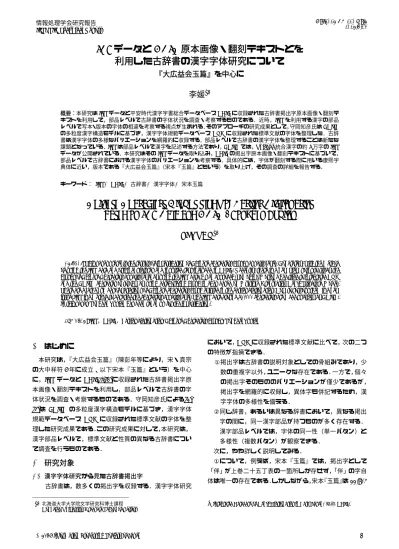
IDSデータとHDIC原本画像・翻刻テキストとを利用した古辞書の漢字字体研究について-『大広益会玉篇』を中心に-
(2) Vol.2016-CH-110 No.6 2016/5/14. 情報処理学会研究報告 IPSJ SIG Technical Report の掲出字が収録される. 「伴」の旁の「半」を含む掲出字は, 「半」 ・ 「畔」 ・ 「伴」などの 21 字がある.原本画像では, 「半」 /「. 」/「. 」との字体があることも確認できる.. 2.3 HDIC 原本画像・翻刻テキスト HDIC では,原本画像から一文字ごとに切り出した画像 を対象としてデータベース化した.掲出字画像データベー. ②は,古辞書において漢字部品レベルで,字体の同一性. スは,漢字字体史研究に利用することを目的として作成し. と多様性とを観察することである.同一性について,同じ. はじめたものである[4].掲出字画像データベースを構築し. 辞書,あるいは異なる辞書の間に,単一パタンだけ存在す. て,掲出字のテキスト入力の効率化をはかる.そして,掲. る部品がある.これらの部品の字体は,同一性があると言. 出字画像データベースによって,掲出字の字形の細部を観. える.多様性について,部品によって,二種類の状況があ. 察できる.宋本玉篇データベースについて,HDIC のプロ. る.一つは,同じ辞書の中バリエーションがあるものであ. ジェクトでは,2014 年にその掲出字と注文とを入力済みで. る.例えば, 「糸」の字体は,高山寺本『篆隷万象名義』の. ある.その後,一次点検・校正の上,宋本『玉篇』のテキ. 「纟」 ・ 「 中,. 」が共存する.もう一つは,一つの辞書では. ストを試行公開中[c]であり,筆者は担当者である.今回の. 同一パタンであるが,異なる辞書の間バリエーションが観. 調査は,試行公開中の掲出字テキストを利用したものであ. 察できる.例えば, 「⺼」の字体は,高山寺本『篆隷万象名. る.宋本玉篇データベースの原本画像は宮内庁書陵部に所. 義』の中, 「⺼」の単一パタンであるが,天治本『新撰字鏡』. 蔵する宋版テキストによった.. の中,「肉」に近い字体である.高山寺本『篆隷万象名義』 と天治本『新撰字鏡』とでは, 「⺼」の多様性が確認できる. さらに,HDIC に収録された古辞書は,古写本と古版本 とがある.古写本は,字体のバリエーションが豊富であり,. 3. 漢字部品に関連する漢字字体の先行研究 漢字字体上の相異が問題になる漢字部品レベルのものが,. 同時に誤写や誤脱を含むものである.原本『玉篇』,高山寺. 今まで関連する各領域の研究成果がある.人文学では,. 本『篆隷万象名義』,天治本『新撰字鏡』,図書寮本『類聚. [5][6][7]は,後漢から魏晋まで,魏晋から隋唐までの書体・. 名義抄』,観智院本『類聚名義抄』はいずれも古写本である.. 字体変化の視点から,多くの実例を集め,『篆隷万象名義』. 古版本は,字体のバリエーションが少なくなり,写本より. の俗字の分析を行い,所用の俗字を共通する文字ごとに. 印刷が鮮明である.掲出字の解読が写本よりしやすい面が. 250 種類に分類した.情報処理では,JIS の包摂規準と UCS. ある.宋本『玉篇』は古版本である.HDIC の作業は,宋本. の IWDS(IRG Working Document Series)が挙げられる.. 『玉篇』の掲出字テキストデータベースを作成し,これを. 守岡知彦氏による[2]は HNG に収録された代表字形デー. 土台として古写本の辞書の作業を進める方針をとっている. タへの IWDS-1[d]を適用した場合の包摂可能性を検討した.. [4].また,字体が翻刻する際に用いる康熙字典体も宋本『玉. 本研究は IDS データを通して,部品レベルで宋本『玉篇』. 篇』に近い.そこで,本研究は古版本である宋本『玉篇』. の掲出字の原本字体の同一性と多様性とを考察するもので. を取り上げ,その漢字字体の実態を考察する.そして,宋. ある.そして,宋本玉篇データベースにおける掲出字符号. 本『玉篇』データベースにおける掲出字符号化する際の包. 化の暗黙的な包摂の実際を整理することによって,包摂規. 摂の実際を整理する.. 準を明確化させようとする.. 2.2 IDS データ. 4. 漢字部品リストの抽出. IDS は部品レベルで漢字を記述する方法である.Unicode では 12 個の漢字構成記述文字 IDC(Ideographic Description Character,⿰⿱⿲⿳⿴⿵⿶⿷⿸⿹⿺⿻,U+2FF0〜U+2FFB) を提供し,これらの IDC によって漢字部品の位置関係を示 すことができる.CHISE では,Unicode 統合漢字の約 7 万 字の IDS データが公開されている[b].IDS は,翻刻の際に, 符号化できない難字を表現する手段である.一方で,大多 数の漢字が IDS データによる記述があるため,IDS データ によって,漢字の部品検索ができる.原本画像と併用する ことによって,部品の原本字体を確認の実現することが可 能となっている.. b) CHISE 漢字構造情報データ http://kanji.zinbun.kyotou.ac.jp/projects/chise/ids/ c) http://hdic.jp d) List of UCV (Unifiable Component Variations) of Ideographs. ⓒ2016 Information Processing Society of Japan. 調査手順は,まず IDS データによって,漢字を構成する 部品を整理する.次に,抽出した漢字の部品を手がかりに して,HDIC の掲出字原本画像・翻刻テキストに基づき,宋 本玉篇における漢字字体のバリエーションを考察する. CHISE で公開する Unicode 統合漢字・基本多言語面の IDS データを利用し,Excel で繰り返してマッチング作業を行 う.この手順によって,次の 534 個のさらに分割できない 基本漢字部品[e]を得られた.ただし,これらの部品の中で は,簡体字による部品も混在し,選別する抽出作業が必要 となる.これらの部品を対象として,宋本『玉篇』の掲出 字の原本字体の調査を行う.. e) なお今回の調査,「咅」のような中間部品や符号化されていない CDP 外 字(台湾中央研究院)などを対象外とした.. 2.
(3) Vol.2016-CH-110 No.6 2016/5/14. 情報処理学会研究報告 IPSJ SIG Technical Report 1. 2. 3. 4. 5. 6. 7. 8. 9. 10. 来. 來. 耂. 老. 乐. 了. 耒. 力. 立. 吏. タ. ⺄. ⺅. ⺆. ⺇. ⺉. ⺊. ⺌. ⺖. ⺘. 241. 242. 243. 244. 245. 246. 247. 248. 249. 250. 11. 12. 13. 14. 15. 16. 17. 18. 19. 20. 隶. 冫. 両. 两. 龙. 龍. 鹵. 鹿. 率. 麻. ⺡. ⺢. ⺣. ⺧. ⺨. ⺩. ⺪. ⺫. ⺭. ⺮. 251. 252. 253. 254. 255. 256. 257. 258. 259. 260. 21. 22. 23. 24. 25. 26. 27. 28. 29. 30. 马. 馬. 𦣝. 毛. 矛. 戼. 门. 門. 米. 糸. ⺯. ⺲. ⺳. ⺶. ⺼. ⻀. ⻃. ⻊. ⻌. ⻏. 261. 262. 263. 264. 265. 266. 267. 268. 269. 270. 31. 32. 33. 34. 35. 36. 37. 38. 39. 40. 丏. 黾. 民. 皿. 黽. 末. 母. 木. 目. 乃. ⻖. ⻗. ⻞. ⻢. ⻤. 凹. 八. 巴. 𡗜. 犮. 271. 272. 273. 274. 275. 276. 277. 278. 279. 280. 41. 42. 43. 44. 45. 46. 47. 48. 49. 50. 內. 内. 年. 卄. 廿. 鸟. 鳥. 乜. 肀. 帇. 白. 办. 半. 勹. 宀. 贝. 貝. 本. 匕. 比. 281. 282. 283. 284. 285. 286. 287. 288. 289. 290. 51. 52. 53. 54. 55. 56. 57. 58. 59. 60. 牛. 牜. 女. 爿. 皮. 片. 丿. 朩. 𣎳. 冖. 必. 㡀. 畢. 釆. 髟. 豳. 秉. 疒. 癶. 卜. 291. 292. 293. 294. 295. 296. 297. 298. 299. 300. 61. 62. 63. 64. 65. 66. 67. 68. 69. 70. 平. 攴. 七. 齐. 齊. 千. 凵. 欠. 且. 青. 不. 才. 艹. 艸. 刂. 冊. 册. 𠕋. 𢆍. 臿. 301. 302. 303. 304. 305. 306. 307. 308. 309. 310. 71. 72. 73. 74. 75. 76. 77. 78. 79. 80. 靑. 丘. 求. 曲. 犬. 隺. 冄. 冉. 人. 刄. 丳. 镸. 長. 厂. 车. 車. 屮. 臣. 辰. 承. 311. 312. 313. 314. 315. 316. 317. 318. 319. 320. 81. 82. 83. 84. 85. 86. 87. 88. 89. 90. 日. 禸. 肉. 入. 卅. 三. 彡. 色. 山. 㚒. 乗. 乘. 尺. 齿. 齒. 彳. 斥. 赤. 虫. 丑. 321. 322. 323. 324. 325. 326. 327. 328. 329. 330. 91. 92. 93. 94. 95. 96. 97. 98. 99. 100. 譱. 丄. 上. 舌. 申. 𦥔. 身. 生. 尸. 𠃜. 豖. 川. 巛. 舛. 串. 垂. 埀. 辵. 朿. 寸. 331. 332. 333. 334. 335. 336. 337. 338. 339. 340. 101. 102. 103. 104. 105. 106. 107. 108. 109. 110. 十. 饣. 石. 史. 矢. 豕. 士. 氏. 礻. 示. 大. 歹. 亻. 卩. 丹. 刀. 丶. 电. 弔. 𢎨. 341. 342. 343. 344. 345. 346. 347. 348. 349. 350. 111. 112. 113. 114. 115. 116. 117. 118. 119. 120. 世. 丗. 亊. 事. 奭. 手. 𦣻. 首. 𠘧. 书. 丁. 鼎. 东. 東. 兜. 斗. 豆. 鬥. 𠁁. 𠂤. 351. 352. 353. 354. 355. 356. 357. 358. 359. 360. 121. 122. 123. 124. 125. 126. 127. 128. 129. 130. 疋. 鼡. 黍. 鼠. 丨. 束. 爽. 水. 氺. 厶. 歺. 噩. 儿. 而. 耳. 二. 犭. 攵. 匚. 方. 361. 362. 363. 364. 365. 366. 367. 368. 369. 370. 131. 132. 133. 134. 135. 136. 137. 138. 139. 140. 巳. 罒. 四. 肃. 粛. 肅. 夊. 𣥂. 田. 㐁. 飞. 非. 飛. 丰. 风. 風. 𦈢. 缶. 夫. 乀. 371. 372. 373. 374. 375. 376. 377. 378. 379. 380. 141. 142. 143. 144. 145. 146. 147. 148. 149. 150. 冂. 头. 凸. 土. 屯. 瓦. 丸. 万. 卐. 卍. 巿. 弗. 甶. 甫. 父. 阜. 丐. 甘. 干. 髙. 381. 382. 383. 384. 385. 386. 387. 388. 389. 390. 151. 152. 153. 154. 155. 156. 157. 158. 159. 160. 亡. 王. 网. 囗. 韦. 为. 為. 韋. 爲. 未. 戈. 革. 鬲. 艮. 𧰨. 更. 工. 弓. 廾. 谷. 391. 392. 393. 394. 395. 396. 397. 398. 399. 400. 161. 162. 163. 164. 165. 166. 167. 168. 169. 170. 亠. 文. 我. 巫. 无. 毋. 㐅. 乄. 五. 兀. 骨. 瓜. 冎. 乖. 卝. 毌. 丱. 广. 龟. 龜. 401. 402. 403. 404. 405. 406. 407. 408. 409. 410. 171. 172. 173. 174. 175. 176. 177. 178. 179. 180. 戊. 夕. 覀. 西. 习. 匸. 卌. 丅. 下. 㔾. 鬼. 𠃌. 果. 禾. 黑. 乎. 虍. 戸. 互. 戶. 411. 412. 413. 414. 415. 416. 417. 418. 419. 420. 181. 182. 183. 184. 185. 186. 187. 188. 189. 190. 乡. 小. 心. 辛. 玄. 穴. 熏. 丫. 牙. 亚. 户. 黄. 黃. 火. 灬. 丌. 及. 亟. 几. 己. 421. 422. 423. 424. 425. 426. 427. 428. 429. 430. 191. 192. 193. 194. 195. 196. 197. 198. 199. 200. 襾. 亜. 亞. 讠. 严. 言. 訁. 央. 羊. 幺. 彐. 彑. 旡. 㡭. 夹. 夾. 甲. 戋. 柬. 见. 431. 432. 433. 434. 435. 436. 437. 438. 439. 440. 201. 202. 203. 204. 205. 206. 207. 208. 209. 210. 爻. 也. 业. 页. 曳. 頁. 一. 衤. 衣. 乁. 見. 纟. 糹. 角. 孑. 疌. 丯. 巾. 斤. 钅. 441. 442. 443. 444. 445. 446. 447. 448. 449. 450. 211. 212. 213. 214. 215. 216. 217. 218. 219. 220. 夷. 𦣞. 乙. 已. 𠂆. 乂. 弋. 义. 邑. 乚. 金. 釒. 井. 丩. 九. 久. 乆. 韭. 臼. 𦥑. 451. 452. 453. 454. 455. 456. 457. 458. 459. 460. 221. 222. 223. 224. 225. 226. 227. 228. 229. 230. 音. 冘. 乑. 𠃊. 尹. 㐆. 廴. 永. 用. 尢. 巨. 亅. 孒. 孓. 夬. 𢇍. 丂. 口. 㐄. 巜. 461. 462. 463. 464. 465. 466. 467. 468. 469. 470. 231. 232. 233. 234. 235. 236. 237. 238. 239. 240. 尤. 由. 酉. 丣. 又. 于. 㬰. 臾. 鱼. 禺. ⓒ2016 Information Processing Society of Japan. 3.
(4) Vol.2016-CH-110 No.6 2016/5/14. 情報処理学会研究報告 IPSJ SIG Technical Report 471. 472. 473. 474. 475. 476. 477. 478. 479. 480. 魚. 予. 羽. 雨. 禹. 玉. 聿. 円. 曰. 曱. 481. 482. 483. 484. 485. 486. 487. 488. 489. 490. 月. 戉. 龠. 𡿧. 𢦏. 兂. 夨. 甴. 乍. 长. 491. 492. 493. 494. 495. 496. 497. 498. 499. 500. 丈. 爪. 爫. 兆. 乛. 氶. 之. 夂. 止. 黹. 501. 502. 503. 504. 505. 506. 507. 508. 509. 510. 豸. 中. 重. 舟. 州. 竹. 专. 丬. 隹. 子. 511. 512. 513. 514. 515. 516. 517. 518. 519. 520. 自. 辶. 𠂇. 阝. 充. 者. 龰. 龴. 龵. 龶. 521. 522. 523. 524. 525. 526. 527. 528. 529. 530. 龷. 龸. 䒑. 𠆢. 𤰔. 𫩏. 𬜯. 具. 冗. 刃. 531. 532. 533. 534. 叟. 旣. 直. 𥄳. 5. 漢字部品から見た字体のバリエーション 対象となる 438 個の部品を調査したところ,原本字体に より,字体の同一性を示す単一パタンの部品と多様性を示 す複数パタンの字体とに分けられる.次に,実例を示しな がら説明する[f]. 5.1 単一パタン (1). 3⺅. IDS. Entry. ⿰⺅司. 伺. ⿰⺅童. 僮. ⿰⺅二. 仁. ⿰⺅虒. 傂. ⿰⺅丕. 伾. IMG. HDIC の掲出字原本画像・翻刻テキストによって,次の 漢字部品,計 96 個を選別し,漢字字体調査の対象外とす る.これ以外 438 個の漢字部品の調査結果を次節で示す. ・簡体字による部品(27 個) 46. 75. 84. 113. 135. 142. 169. 195. 198. 200. 贝. 车. 齿. 东. 风. 弗. 龟. 夹. 戋. 见. 202. 210. 235. 251. 276. 332. 364. 372. 386. 424. 纟. 钅. 乐. 马. 鸟. 饣. 肃. 头. 为. 讠. 425. 434. 448. 469. 490. 严. 页. 义. 鱼. 长. (2). 6⺉. ・原本字体に含まれない部品(44 個) 17. 33. 35. 69. 71. 97. 110. 127. 131. 139. ⺪. ⻞. ⻤. 𢆍. 丳. 埀. 𢎨. 犭. 飞. 夫. 150. 212. 217. 224. 243. 244. 245. 262. 274. 278. 髙. 釒. 乆. 孓. 両. 两. 龙. 黾. 卄. 乜. 279. 294. 310. 343. 345. 350. 352. 365. 385. 398. 肀. 齐. 刄. 亊. 奭. 书. 鼡. 粛. 韦. 乄. 405. 418. 422. 423. 427. 456. 478. 480. 488. 507. 习. 丫. 亜. 亞. 訁. 㐆. 円. 曱. 甴. 专. 508. 524. 526. 527. 丬. 𠆢. 𫩏. 𬜯. IDS. Entry. ⿰𠮠⺉. 別. ⿰萠⺉. 蒯. ⿰茾⺉. 荆. ⿰肖⺉. 削. ⿰奇⺉. 剞. IMG. ・原本字体に孤例である部品(25 個) 1. 4. 13. 56. 80. 98. 167. 178. 223. 231. タ. ⺆. ⺣. 豳. 承. 辵. 丱. 戸. 孒. 来. 257. 301. 315. 321. 322. 342. 378. 379. 380. 403. 丗. 万. 卐. 卍. 覀. 门. 靑. 卅. 譱. 丄. 406. 407. 420. 484. 522. 匸. 卌. 亚. 𡿧. 龸. 一部の原本字体しか示さないが, 「⺅」と「⺉」の字体 は,宋本『玉篇』ではすべて異同がない.原本字体のレベ ルでは,単一パタンであることが確認できる. 単一パタンであることが確認できた漢字部品は次の 237 個がある.宋本『玉篇』において,これらの部品は,字体 の同一性が確認できた.. f) 例示する「⺅」「⺉」「巴」「甘」等の部品をもちいる掲出字の翻字は, [8]に収録された宋本『玉篇』の翻刻テキストと一致する.. ⓒ2016 Information Processing Society of Japan. 4.
(5) Vol.2016-CH-110 No.6 2016/5/14. 情報処理学会研究報告 IPSJ SIG Technical Report 䒑. 具. 冗. 刃. 旣. 直. 3. 6. 9. 10. 14. 15. 16. 20. 21. 22. ⺅. ⺉. ⺖. ⺘. ⺧. ⺨. ⺩. ⺮. ⺯. ⺲. 25. 27. 28. 29. 30. 31. 32. 36. 39. 45. ⺼. ⻃. ⻊. ⻌. ⻏. ⻖. ⻗. 凹. 𡗜. 宀. 50. 52. 53. 55. 57. 58. 59. 64. 65. 67. 比. 㡀. 畢. 髟. 秉. 疒. 癶. 艸. 刂. 册. 68. 72. 73. 81. 82. 83. 85. 86. 87. 88. 𠕋. 镸. 長. 乗. 乘. 尺. 齒. 彳. 斥. 赤. 89. 91. 92. 94. 100. 102. 103. 104. 108. 109. 虫. 豖. 川. 舛. 寸. 歹. 亻. 卩. 电. 弔. 111. 112. 114. 116. 117. 120. 122. 124. 129. 130. 丁. 鼎. 東. 斗. 豆. 𠂤. 噩. 而. 匚. 方. 132. 133. 134. 136. 137. 145. 149. 152. 154. 155. 非. 飛. 丰. 風. 𦈢. 父. 干. 革. 艮. 𧰨. 156. 157. 160. 161. 162. 166. 168. 173. 180. 181. 更. 工. 谷. 骨. 瓜. 毌. 广. 果. 戶. 户. 184. 185. 187. 188. 194. 197. 201. 203. 209. 211. 火. 灬. 及. 亟. 㡭. 甲. 見. 糹. 斤. 金. 215. 218. 225. 226. 229. 232. 233. 234. 236. 237. 九. 韭. 夬. 𢇍. 㐄. 來. 耂. 老. 了. 耒. 239. 240. 246. 247. 248. 249. 250. 252. 254. 258. 立. 吏. 龍. 鹵. 鹿. 率. 麻. 馬. 毛. 門. 260. 263. 264. 265. 268. 269. 270. 272. 273. 277. 糸. 民. 皿. 黽. 木. 目. 乃. 内. 年. 鳥. 281. 282. 283. 285. 286. 287. 290. 291. 298. 300. 牛. 牜. 女. 皮. 片. 丿. 冖. 平. 欠. 青. 304. 305. 306. 311. 312. 316. 317. 318. 319. 325. 曲. 犬. 隺. 日. 禸. 三. 彡. 色. 山. 申. 326. 327. 328. 330. 331. 333. 334. 336. 337. 338. 𦥔. 身. 生. 𠃜. 十. 石. 史. 豕. 士. 氏. 339. 340. 341. 344. 346. 347. 351. 353. 356. 359. 礻. 示. 世. 事. 手. 𦣻. 疋. 黍. 束. 氺. 361. 362. 367. 374. 375. 381. 382. 384. 387. 389. 巳. 罒. 夊. 土. 屯. 亡. 王. 囗. 為. 爲. 393. 394. 395. 396. 397. 399. 409. 411. 413. 417. 我. 巫. 无. 毋. 㐅. 五. 下. 乡. 心. 熏. 419. 421. 426. 428. 430. 431. 432. 433. 435. 436. 牙. 襾. 言. 央. 幺. 爻. 也. 业. 曳. 頁. 「巴」と「甘」の字体は,宋本『玉篇』ではそれぞれ二. 437. 439. 441. 443. 444. 445. 446. 447. 450. 451. つのパタンが観察される.原本字体レベルでは,複数パタ. 一. 衣. 夷. 乙. 已. 𠂆. 乂. 弋. 乚. 音. ンであることが確認できた.. 453. 455. 460. 466. 470. 473. 475. 479. 483. 489. 複数パタンであることが確認できた漢字部品は次の 201. 乑. 尹. 尢. 于. 禺. 羽. 禹. 曰. 龠. 乍. 個がある.宋本『玉篇』において,これらの部品は,字体. 491. 496. 497. 499. 500. 501. 502. 503. 505. 509. の多様性が確認できる.. 丈. 氶. 之. 止. 黹. 豸. 中. 重. 州. 隹. 511. 512. 513. 514. 515. 516. 517. 519. 520. 自. 辶. 𠂇. 阝. 充. 者. 龰. 龵. 龶. 523. 525. 528. 529. 530. 532. 533. ⓒ2016 Information Processing Society of Japan. 𤰔. 5.2 複数パタン (3) 38 巴 IDS. Entry. ⿰⺼巴. 肥. ⿰. 巴. 𣥘. ⿰立巴. 𥩙. ⿸戶巴. 𢨴. ⿰木巴. 杷. IMG. (4) 148 甘 IDS. Entry. ⿱弋甘. 𤮼. ⿰甘覃. 㽑. ⿰甘兼. 㽐. ⿱. 甘. 甞. ⿱干甘. 𤮻. IMG. 2. 5. 7. 8. 11. 12. 18. 19. 23. 24. 521. ⺄. ⺇. ⺊. ⺌. ⺡. ⺢. ⺫. ⺭. ⺳. ⺶. 龷. 26. 37. 38. 40. 41. 43. 44. 47. 48. 49. ⻀. 八. 巴. 犮. 白. 半. 勹. 貝. 本. 匕. 5.
(6) Vol.2016-CH-110 No.6 2016/5/14. 情報処理学会研究報告 IPSJ SIG Technical Report 51. 54. 60. 61. 62. 63. 66. 70. 74. 76. 438 個の基本部品のうち,237 個の部品に対応する漢字. 必. 釆. 卜. 不. 才. 艹. 冊. 臿. 厂. 車. 字体は宋本『玉篇』において,単一パタンであり,字体の. 77. 78. 79. 90. 93. 95. 96. 99. 101. 105. 同一性が確認できた.201 個の部品に対応する漢字字体は. 屮. 臣. 辰. 丑. 巛. 串. 垂. 朿. 大. 丹. 宋本『玉篇』ではバリエーションが観察され,字体の多様. 106. 107. 115. 118. 119. 121. 123. 125. 126. 128. 性が確認できた.. 刀. 丶. 兜. 鬥. 𠁁. 歺. 儿. 耳. 二. 攵. さらに,これらバリエーションが観察される 201 個の部. 138. 140. 141. 143. 144. 146. 147. 148. 151. 153. 品に対応する宋本『玉篇』の字体を整理し,宋本玉篇デー. 缶. 乀. 巿. 甶. 甫. 阜. 丐. 甘. 戈. 鬲. タベースにおける掲出字符号化の包摂の実際を整理した.. 158. 159. 163. 164. 165. 170. 171. 172. 174. 175. 今後,中間部品と外字とも取り込み,それによって,宋. 弓. 廾. 冎. 乖. 卝. 龜. 鬼. 𠃌. 禾. 黑. 本玉篇データベースにおける掲出字符号化の包摂の実際を. 176. 177. 179. 182. 183. 186. 189. 190. 191. 192. 考察する必要がある.さらに,IWDS と JIS 包摂規準とを. 乎. 虍. 互. 黄. 黃. 丌. 几. 己. 彐. 彑. 取り上げ,これらの包摂規準と宋本玉篇データベースの掲. 193. 196. 199. 204. 205. 206. 207. 208. 213. 214. 出字符号化の包摂の実際とを比較する.そして,IWDS と. 旡. 夾. 柬. 角. 孑. 疌. 丯. 巾. 井. 丩. JIS 包摂規準を宋本『玉篇』の掲出字符号化の作業に適用と. 216. 219. 220. 221. 222. 227. 228. 230. 238. 241. する場合,どのように拡張すべきかを検討したい.. 久. 臼. 𦥑. 巨. 亅. 丂. 口. 巜. 力. 隶. 242. 253. 255. 256. 259. 261. 266. 267. 271. 275. 冫. 𦣝. 矛. 戼. 米. 丏. 末. 母. 內. 廿. 280. 284. 288. 289. 292. 293. 295. 296. 297. 299. 参考文献 [1]. 池田証壽. 平安時代漢字字書総合データベースの構築.北海. 帇. 爿. 朩. 𣎳. 攴. 七. 齊. 千. 凵. 且. 302. 303. 307. 308. 309. 313. 314. 320. 323. 324. 丘. 求. 冄. 冉. 人. 肉. 入. 㚒. 上. 舌. 329. 335. 348. 349. 354. 355. 357. 358. 360. 363. 尸. 矢. 首. 𠘧. 鼠. 丨. 爽. 水. 厶. 四. 366. 368. 369. 370. 371. 373. 376. 377. 383. 388. –漢字字体規範データベースの CHISE への収録を通じて. 人文科学とコンピュータシンポジウム 2015 論文集.情報処. 肅. 𣥂. 田. 㐁. 冂. 凸. 瓦. 丸. 网. 韋. 390. 391. 392. 400. 401. 402. 404. 408. 410. 412. 未. 亠. 文. 兀. 戊. 夕. 西. 丅. 㔾. 小. 414. 415. 416. 429. 438. 440. 442. 449. 452. 454. 辛. 玄. 穴. 羊. 衤. 乁. 𦣞. 邑. 冘. 𠃊. 457. 458. 459. 461. 462. 463. 464. 465. 467. 468. 廴. 永. 用. 尤. 由. 酉. 丣. 又. 㬰. 臾. 471. 472. 474. 476. 477. 481. 482. 485. 486. 487. 魚. 予. 雨. 玉. 聿. 月. 戉. 𢦏. 兂. 夨. 492. 493. 494. 495. 498. 504. 506. 510. 518. 531. 爪. 爫. 兆. 乛. 夂. 舟. 竹. 子. 龴. 叟. 534. 道大学文学研究科紀要.2014,vol. 142,pp. 79-90. [2]. 守岡知彦.長安宮廷写経の漢字字体と包摂規準 – HNG と CHISE の統合を通じて−.東洋学へのコンピュータ利用 第 27 回研究セミナー.2016,pp. 15-48.. [3]. 守岡知彦.多粒度漢字構造モデルに基づく字形整理の試み. 理学会.2015,pp. 1-8. [4]. 池田証壽. 『大広益会玉篇』データベースの構築と利用―『篆 隷万象名義』 『新撰字鏡』 『大宋重修広韻』との対応―.情報 科学と言語研究.現代図書.2016,pp. 65-84.. [5]. 大柴清圓. 『篆隷萬象名義』における俗字の研究(1)―後漢 の隷変字から魏晋の草書の楷書化まで―.高野山大学密教 文化研究所紀要.2008,vol. 21,pp. 49-100.. [6]. 大柴清圓. 『篆隷万象名義』における俗字の研究(2)―魏晋 から隋唐までの楷書の俗字―.高野山大学密教文化研究所紀 要.2009,vol. 22,pp. 227-284.. [7]. 𥄳. 大柴清圓. 『篆隷万象名義』における俗字の研究(3)―附 録・ 『篆隷万象名義』俗字表―. 高野山大学密教文化研究所紀 要.2011,vol. 24,pp. 93-138.. 6. おわりに. [8]. 古佚三書上元本玉篇/韻/小學鈎沉三編.四川出版集團. 四川辭書出版社.2013,pp. 1011-1562.. 本研究は,CHISE で公開する Unicode 統合漢字・基本多 言語面の IDS データを利用し,さらに分割できない基本漢 字部品リストを得られた.簡体字による部品,宋本『玉篇』 に含まれない部品,宋本『玉篇』では孤例である部品以外, 438 個のものを対象にし,部品検索によって,HDIC に収録 された宋本玉篇の原本画像を利用し,宋本『玉篇』の漢字 字体の実態を考察した.. ⓒ2016 Information Processing Society of Japan. 6.